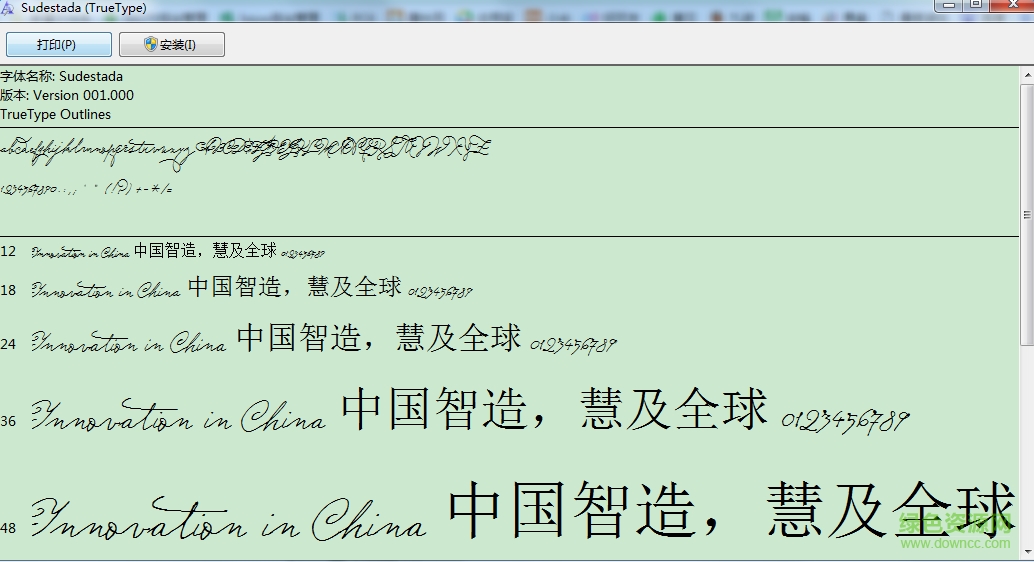
sudestada字體非常有特色的藝術(shù)字體,這款字體筆畫纖細(xì),字體字形花哨,非常適用于個(gè)性簽名,喜歡這款字體的朋友歡迎來綠色資源網(wǎng)下載體驗(yàn)。
sudestada是一款特色的簽字字體,筆畫連綿,整個(gè)書寫看著比較有曲線,非常引人注目,常常用于藝術(shù)設(shè)計(jì)方面!